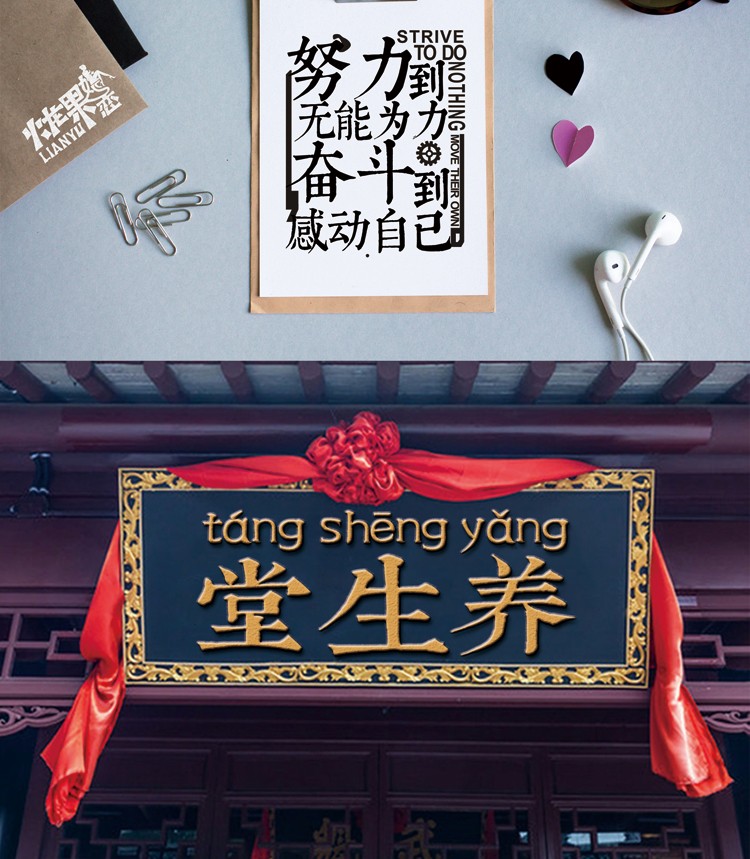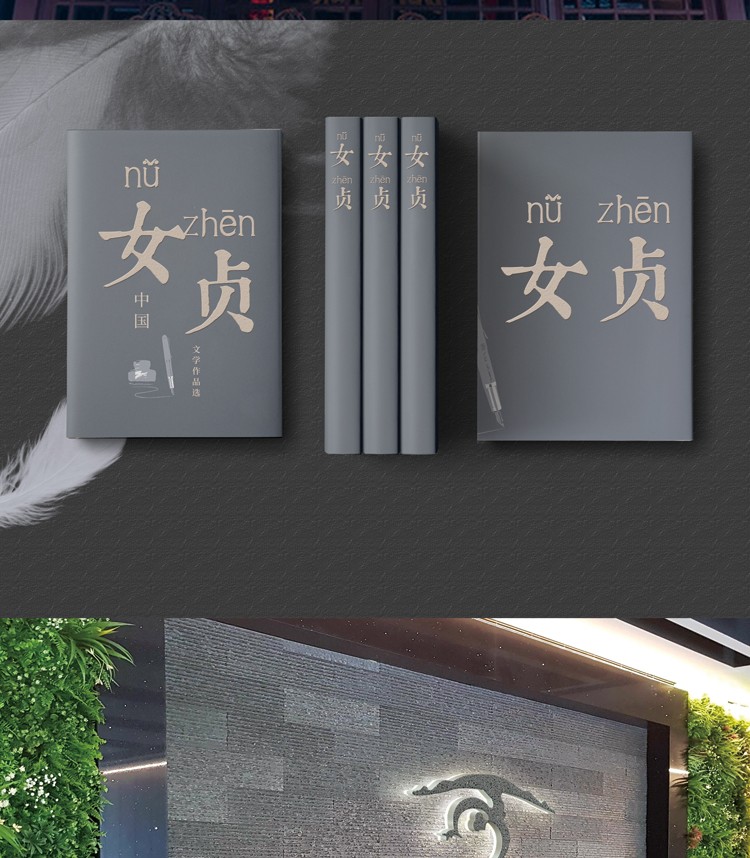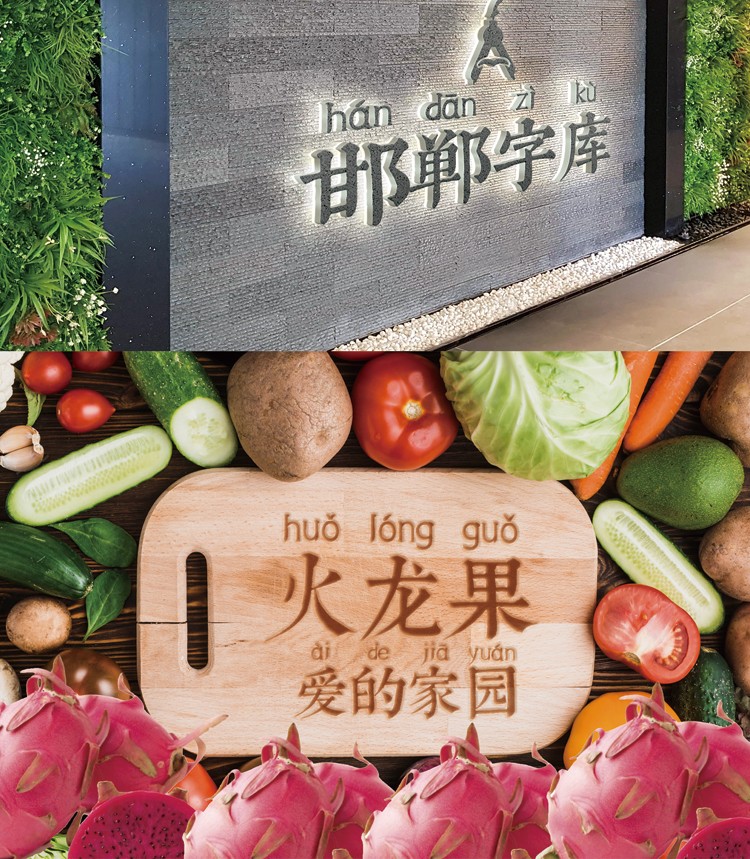
邯鄲康熙字典注音體 詳情頁
字體名稱: 邯鄲康熙字典注
邯鄲康熙字典注音體
繁簡精全共47549字
邯鄲康熙字典注音體字體邯鄲康熙字典注音體【繁簡精全47549字】字庫是一款讓人賞心悅目、百看不厭的中文字體,適合各類廣告和產(chǎn)品包裝設(shè)計應(yīng)用,字體大小79.38MB,格式為ttf字體,上傳用戶是邯鄲字庫,作者/版權(quán)方為韓紹杰